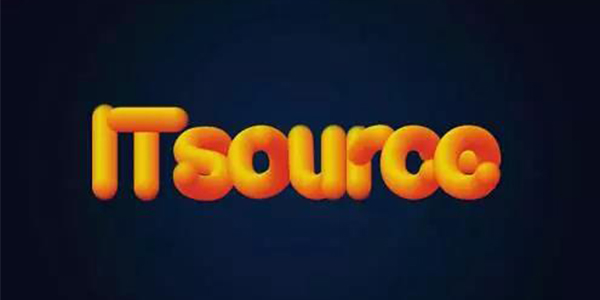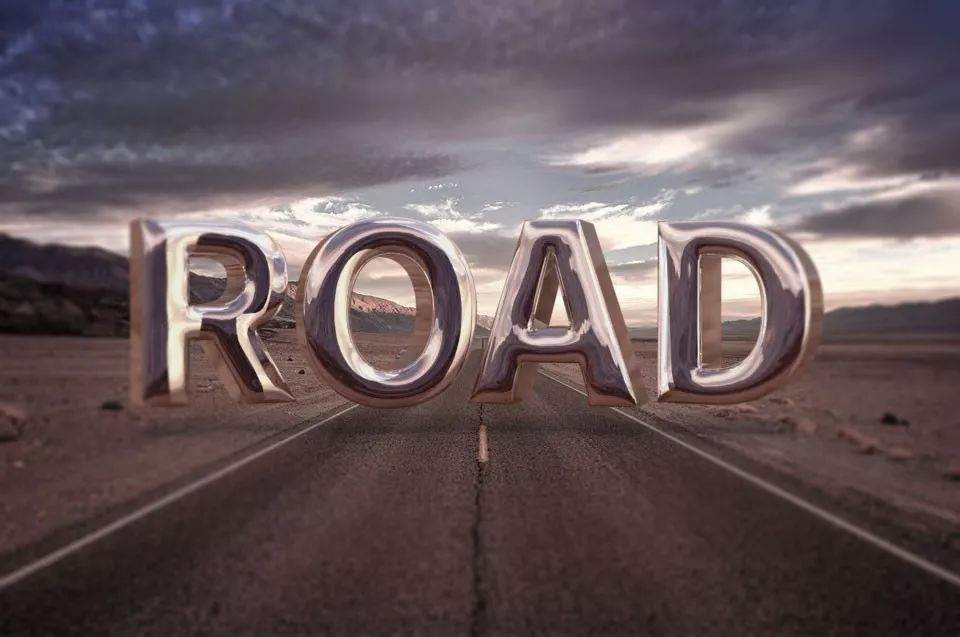
3分钟做出3D效果!使用PS做出3D效果教程
平面设计师不学 3D
真的就没有职业发展空间吗?
前段时间,美丫姐收到粉丝投稿
提到关于平面设计师学3D的问题
同期进公司的同事
就因为会3D,工资整整比自己高一倍
看似夸张,其实也不难理解
大家都喜欢视觉效果更好的设计
会 3D 的平面设计师自然更吃香
可C4D、犀牛、Maya无论哪个3D软件
入门门槛都高得吓人
学个个把月都不一定能建好模
更别说设计师平常根本没时间琢磨
就算时间充裕,电脑也未必带得起
平面设计师想学3D就这么难吗?
其实并不然!用PS就能轻松搞定
基础3D效果完全不输3D软件
接下来美丫姐就教大家
8步在PS里制作下面这张超现实场景!
1/建模
选中文字图层,「3D-从图层新建3D模型」
点选「形状预设」,让文字更圆润
除了这个,而且PS还内置预设模型
点击「3D-从图层新建网格-网格预设」
即可一秒建模!再也不用费时找样机
2/材质处理
在3D标签下,选中所需图层
将「反射」调到最高
选择「环境」图层,移除纹理
再点击「新建纹理」
最后点选「编辑纹理」
将底图复制到跳出窗口中,ctrl+s保存
返回原来界面,调整好反射角度
如果不喜欢这种材质
还有各类现成材质可以选用
3/光影&位置
选「无限光」调整光影角度
点击「颜色」吸取画面色彩
让文字更融入画面氛围
选中文字图层,点击「3D-拆分突出」
单独微调字母位置和角度
4/渲染&调色
将字母调整到满意状态后
点击「3D-渲染3D图层」就能渲染啦!
最后回到图层标签下
给背景和字体适当调调色就能完工!
怎么样,是不是特别简单?
不用面对复杂的3D软件
还能帮你节省下不少时间